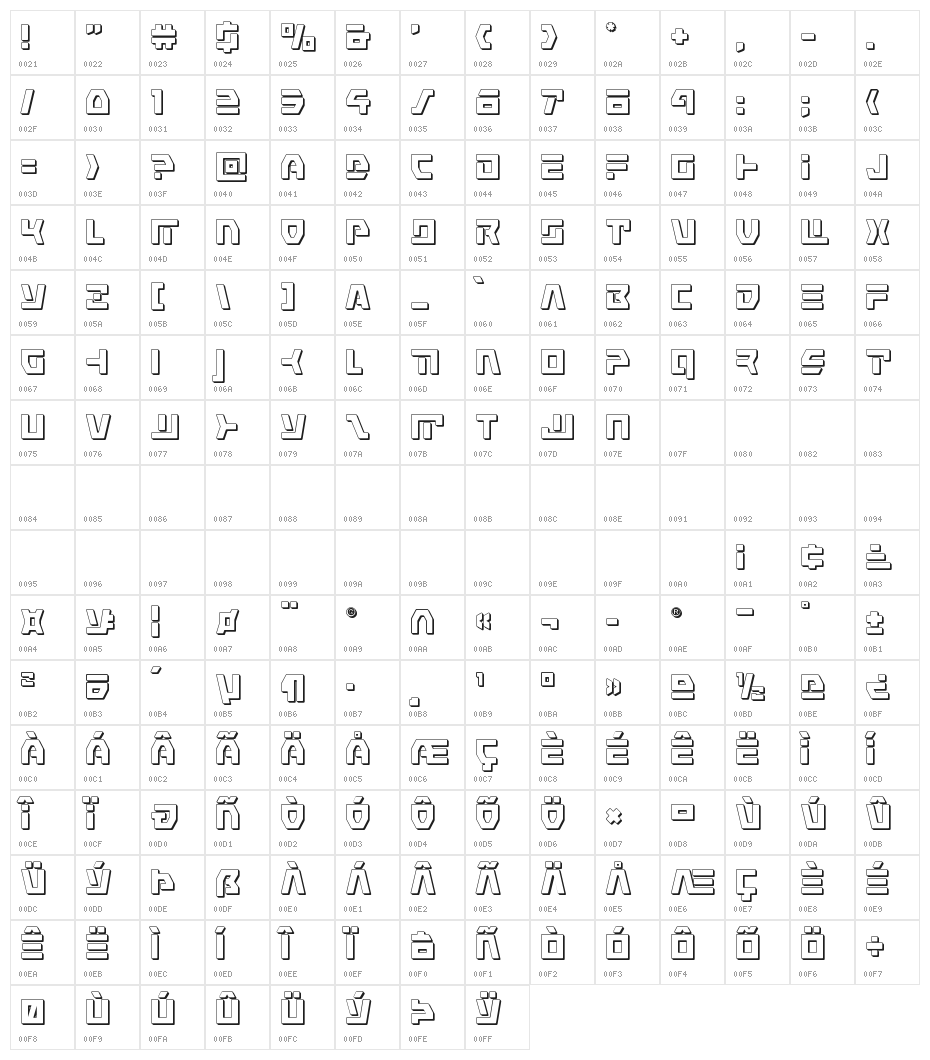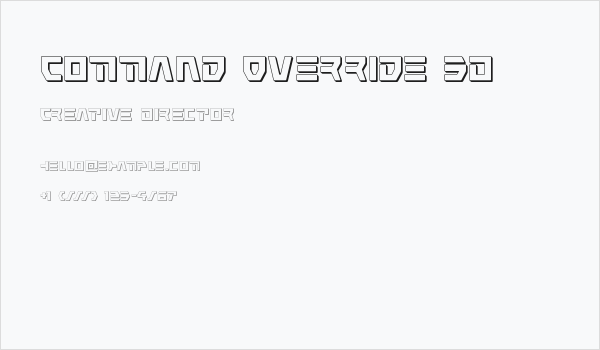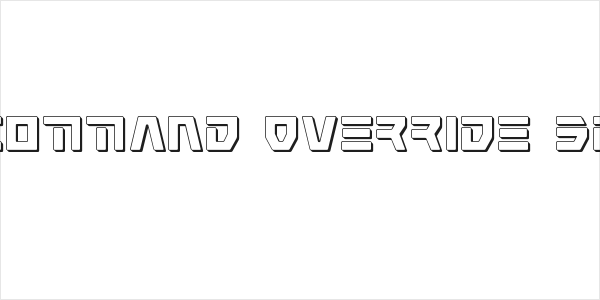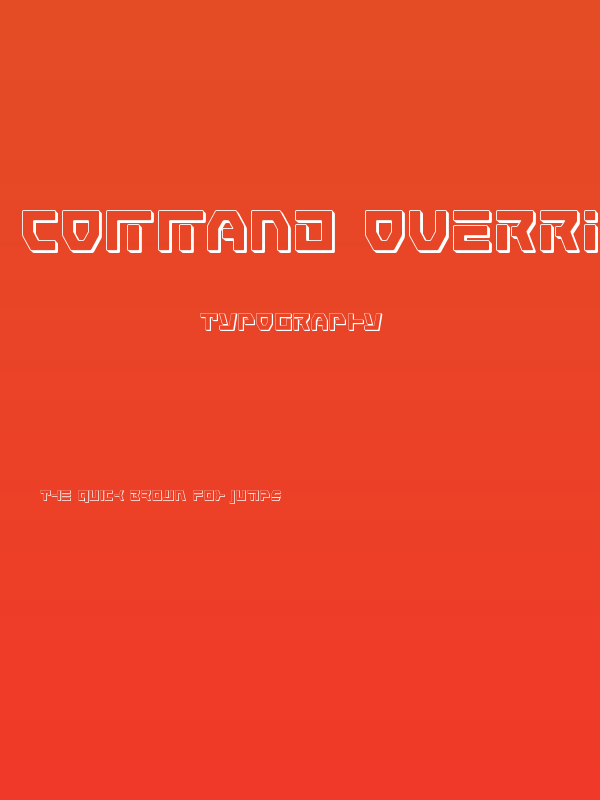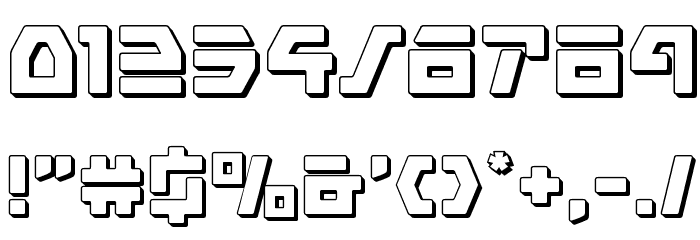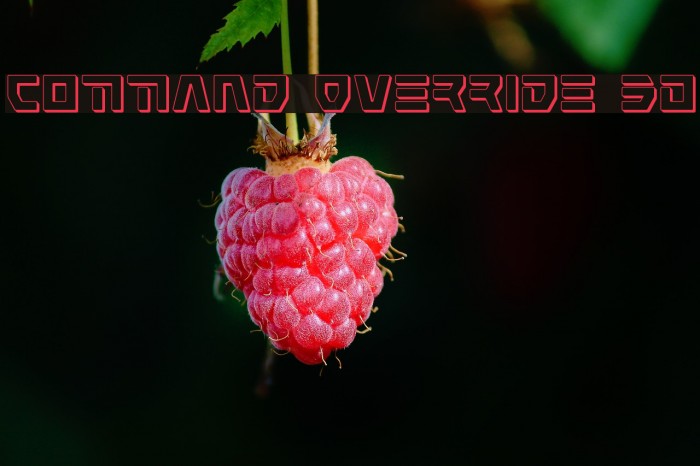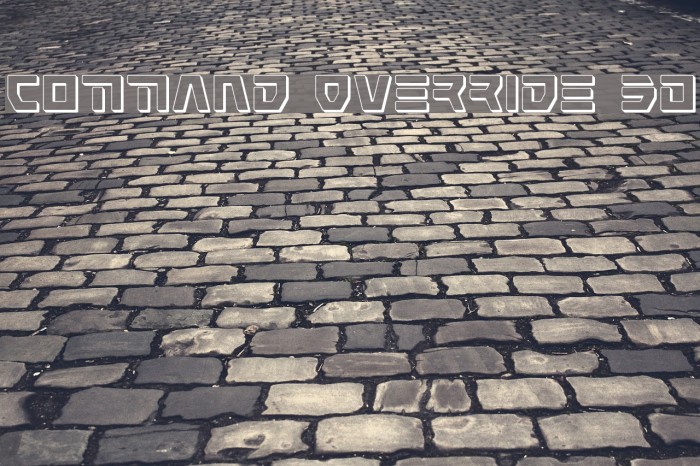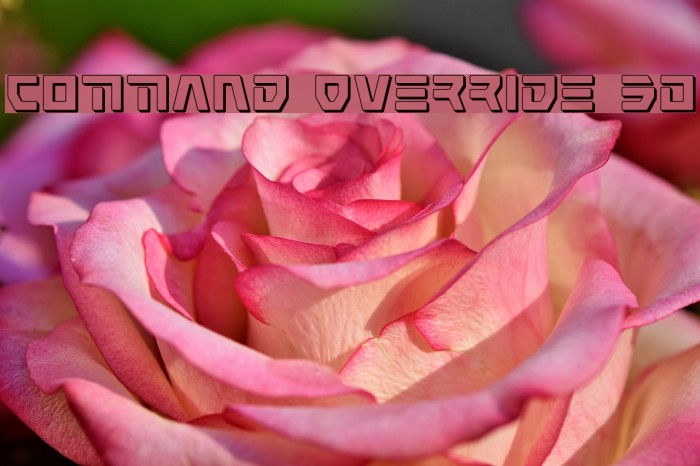
Command Override 3D Font
✎ Outline
| Categorías | Outline |
| Proyectos propuestos | Ideal for sci-fi movie posters, video game titles, tech company logos, and digital art projects. |